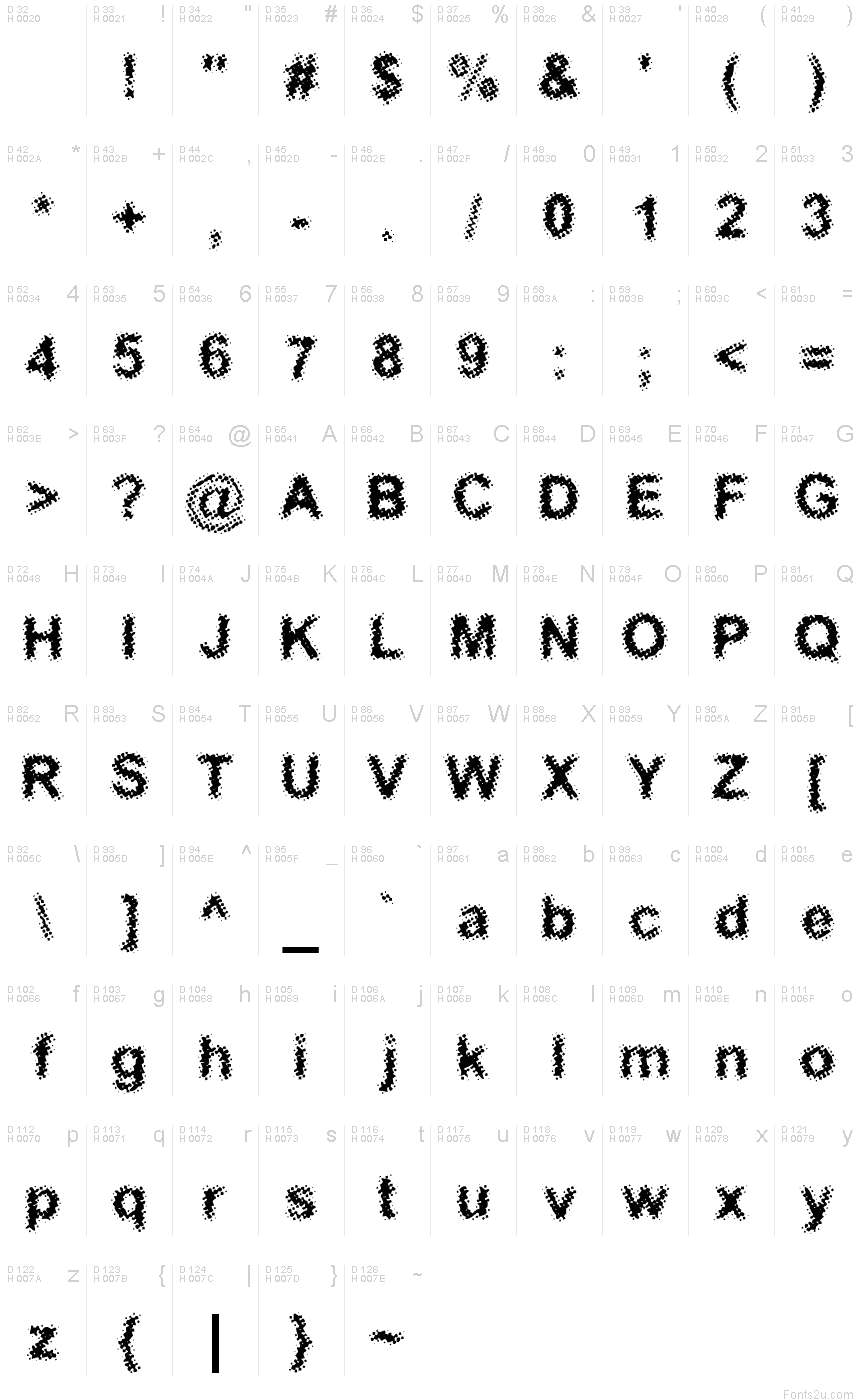
Acidic od Surface Design Group to darmowy krój pisma typu display o erodowanym wyglądzie, przypominający litery potraktowane chemikaliami i pozostawione do wyżarcia. Masywne, czarne formy są podziurawione skupiskami ostrych, okrągłych otworów, co tworzy musującą, korozyjną teksturę – jednocześnie zabawną i niebezpieczną. Litery pozostają pogrubione i czytelne, ale ich powierzchnia wygląda na zniszczoną i niestabilną, jakby ciągle rozpuszczały się na stronie.
Acidic to darmowy font, który błyskawicznie wprowadza toksyczną energię do plakatów horrorów, klubowych ulotek, okładek płyt grunge, eksperymentalnego brandingu, tytułów gier i wyrazistych grafik w mediach społecznościowych. Najlepiej sprawdza się w dużych rozmiarach, gdzie widać każdą wyszczerbioną krawędź i rozproszony „odprysk”. Zestawiaj go z czystym, neutralnym krojem bezszeryfowym w tekście głównym, dzięki czemu Acidic poradzi sobie z głośnymi, chaotycznymi nagłówkami, nie przytłaczając reszty układu.